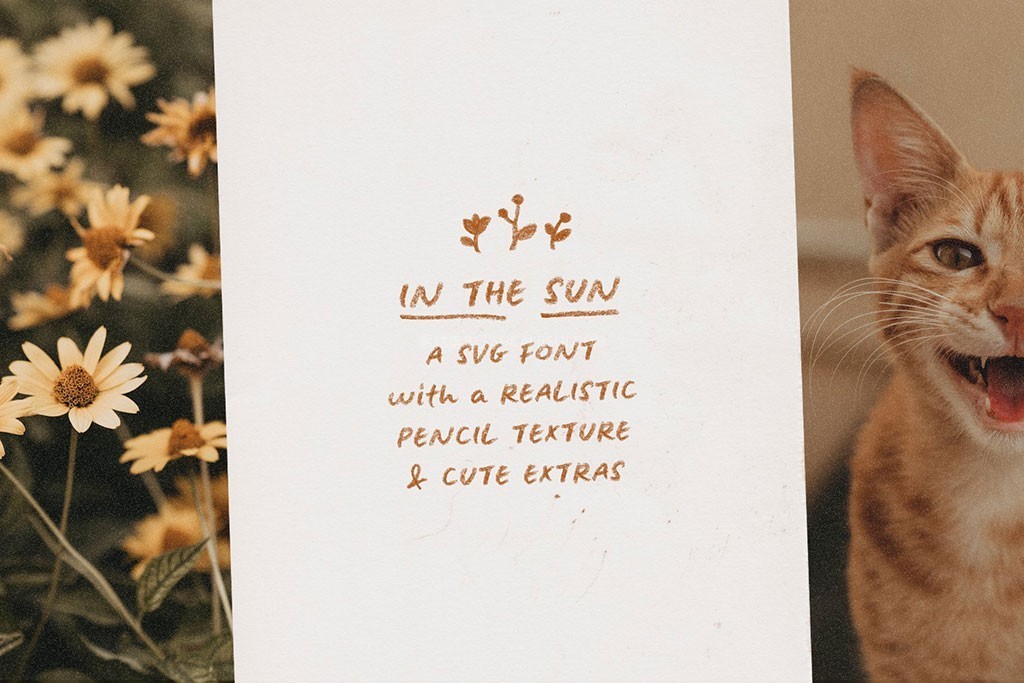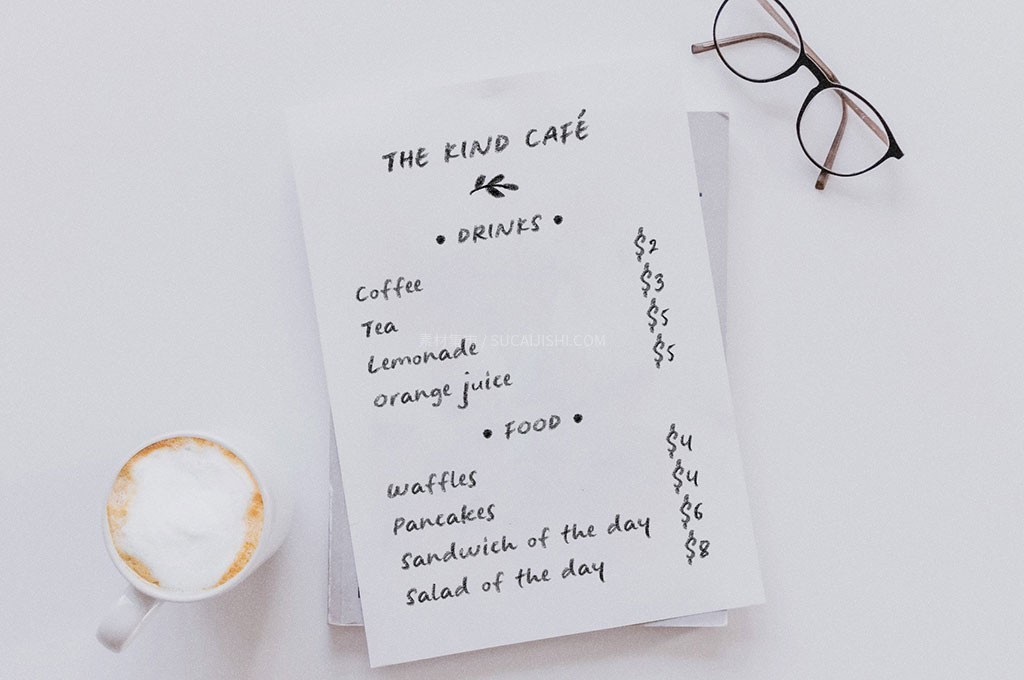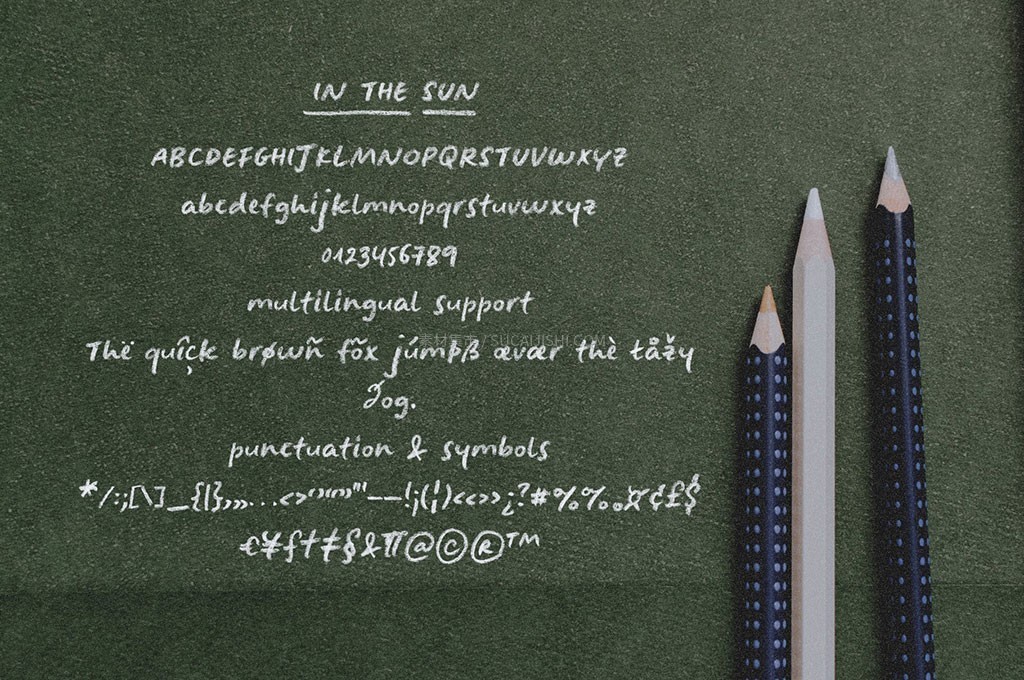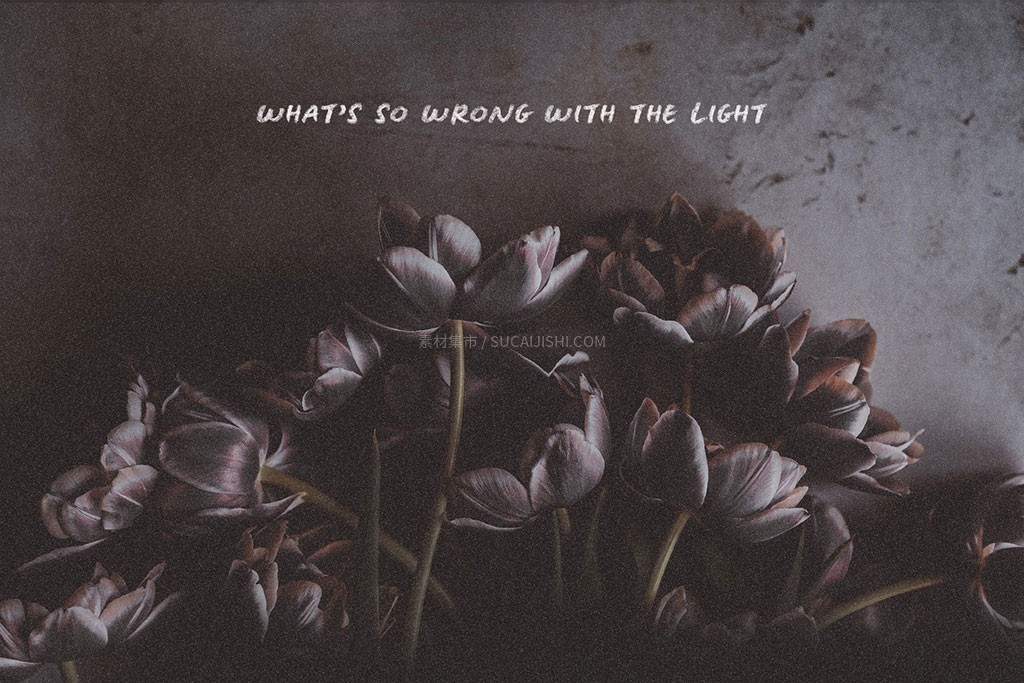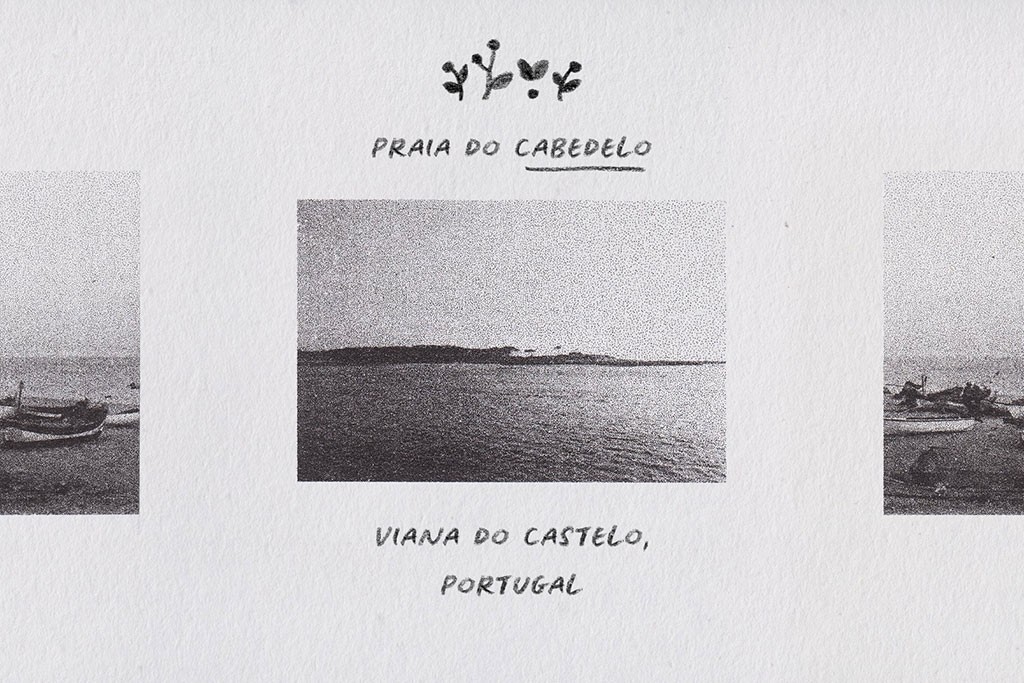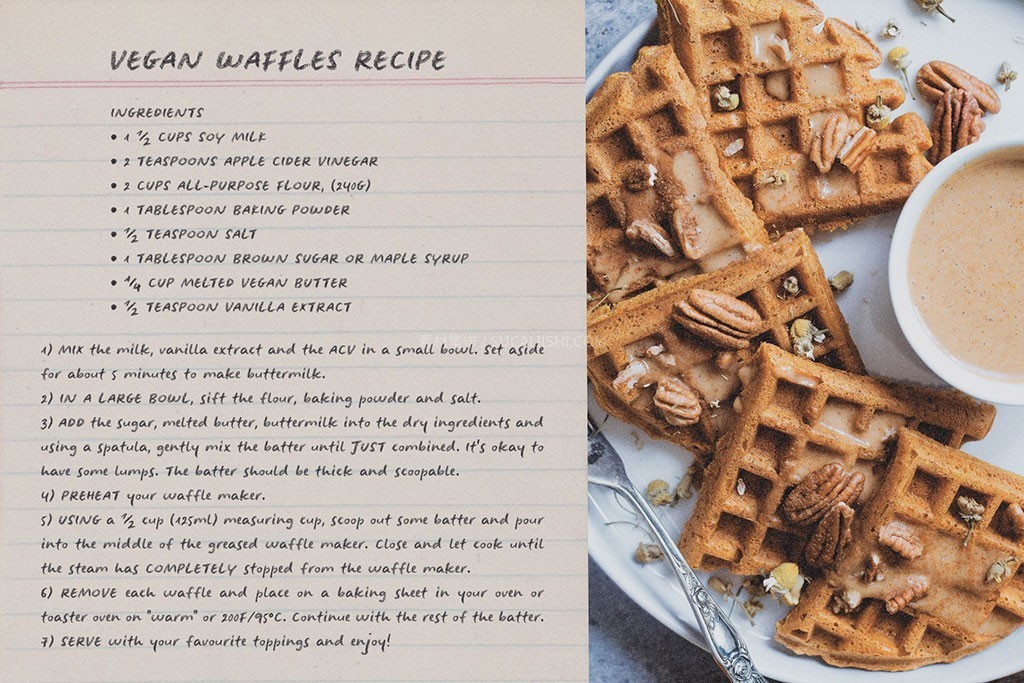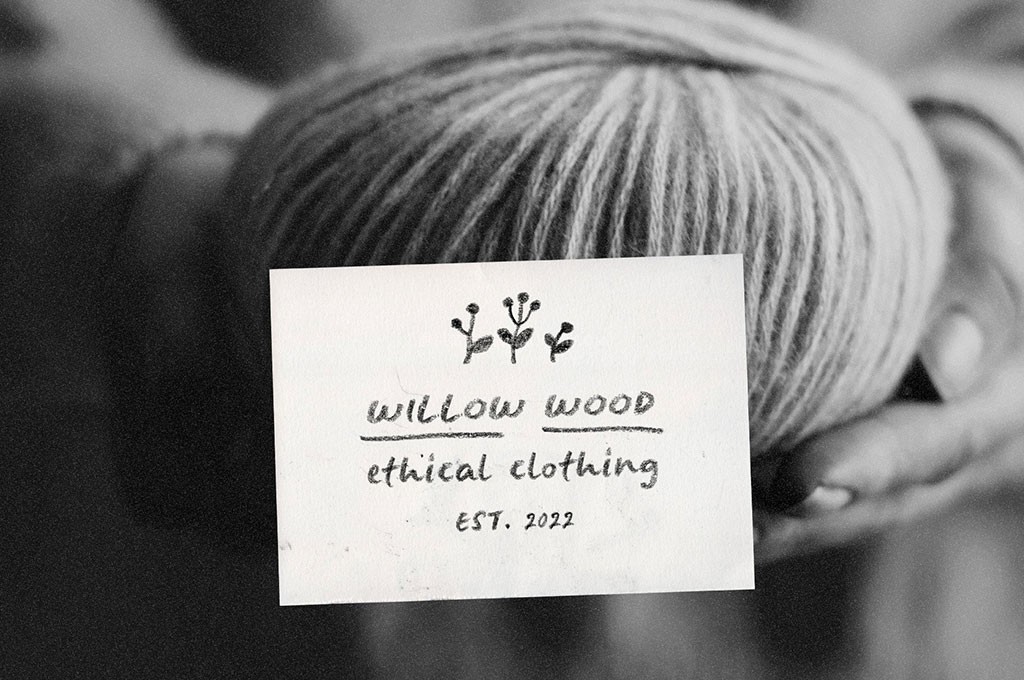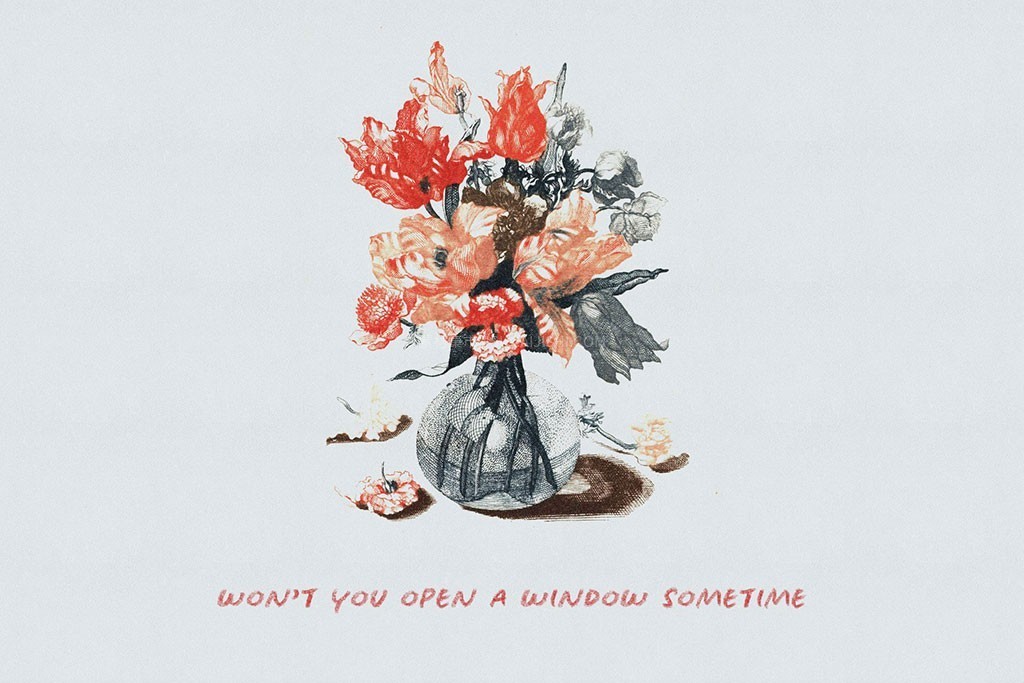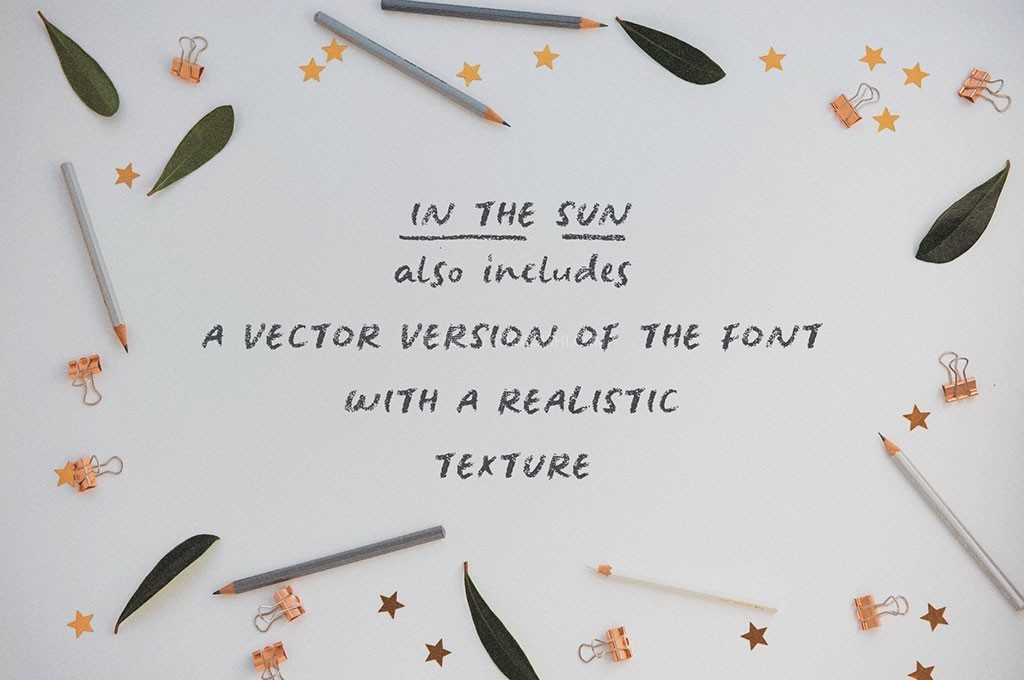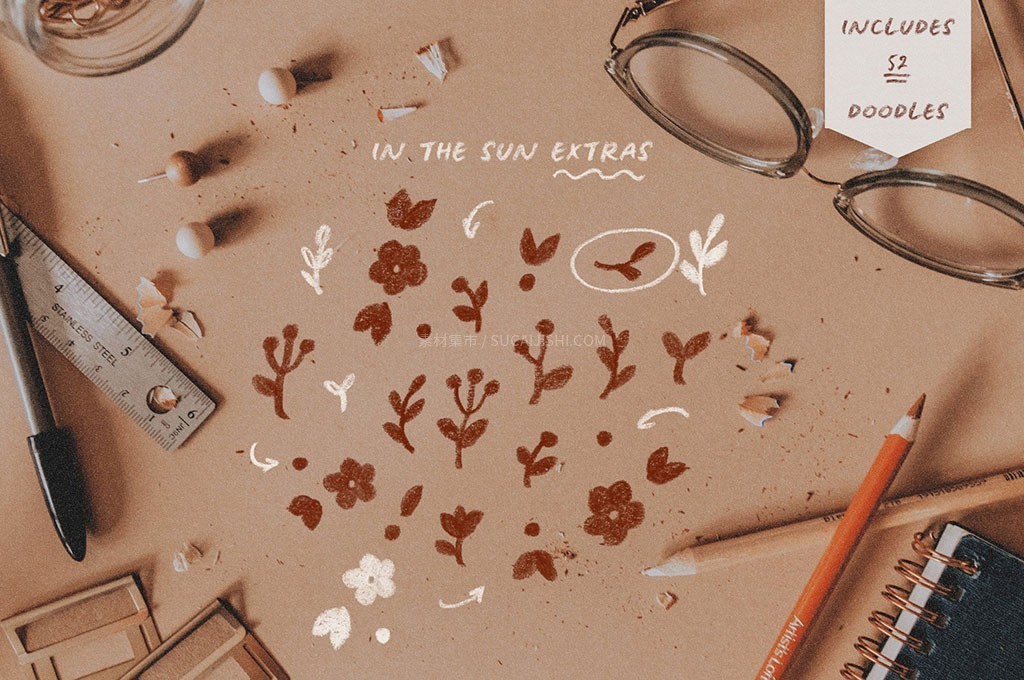
In The Sun 治愈系手绘铅笔质感SVG字体
一款充满治愈感的铅笔手写涂鸦SVG字体!它完美还原了真实的铅笔细腻纹理,在小字号和全大写排版下视觉效果绝佳。不仅有主字体,还附带了超级实用的 Extras 涂鸦符号库(包含下划线、圆圈、箭头和可爱的手绘小花)。
In The Sun 治愈系手绘铅笔质感SVG字体